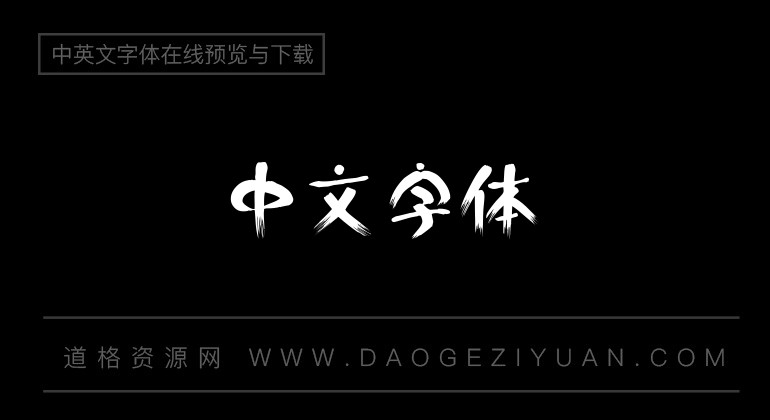
方圆白雨体
方圆白雨体是一款汉字行楷体字体,它是由湖南方圆文化传播有限公司设计的。这款字体以汉代的楷书为基础,结合现代设计理念,融合了汉字的传统美感和现代美感,让汉字更加美观大方。它的特点是字母清晰,边缘细腻,线条流畅,能够表达出汉字的精细与细腻,具有良好的可读性,可以用于书法、广告、文章等场景。
方圆白雨体是一款非常不错的手写艺术字体,具有很好的视觉感,适合于文化类的宣传设计、商业类品牌的广告和产品包装设计以及个性化文字排版等较多场景。